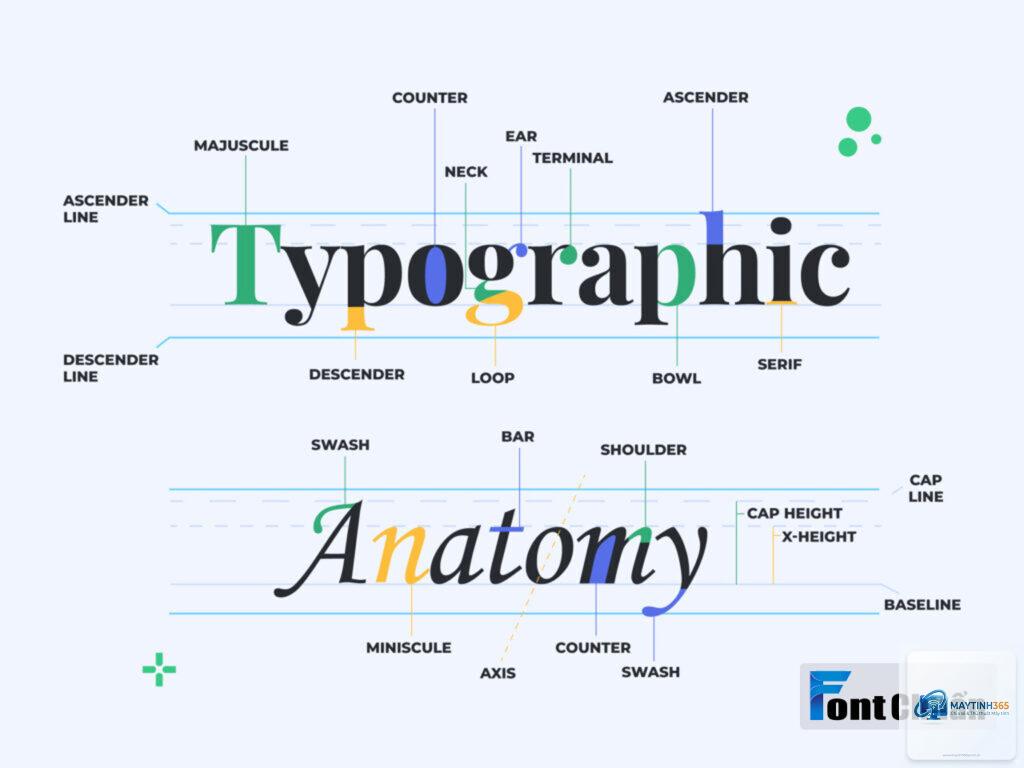
Cách cá nhân hóa font chữ để tạo dấu ấn riêng cho website và thương hiệu
Cá nhân hóa font chữ không chỉ đơn thuần là thay đổi kiểu chữ trên màn hình. Đây là một chiến lược thiết kế giúp thương hiệu truyền tải cá tính, tăng nhận diện và cải thiện trải nghiệm người dùng. Trong thời đại mà hàng triệu website cạnh tranh nhau từng giây, việc sở hữu một bộ font chữ độc đáo có thể là yếu tố quyết định giữ chân khách truy cập. Bài viết này sẽ hướng dẫn bạn cách cá nhân hóa font chữ từ cơ bản đến nâng cao, áp dụng cho website, ứng dụng và nội dung số.
Cá nhân hóa font chữ là gì và tại sao cần thực hiện
Cá nhân hóa font chữ là quá trình tùy chỉnh kiểu chữ, kích thước, màu sắc, khoảng cách và các thuộc tính khác để phù hợp với mục đích sử dụng cụ thể. Không giống như việc chọn một font chữ mặc định từ hệ thống, cá nhân hóa đòi hỏi sự can thiệp sâu hơn vào cấu trúc thiết kế.
Mỗi font chữ mang một tâm trạng riêng. Font serif cổ điển tạo cảm giác trang trọng, font sans-serif hiện đại thể hiện sự tối giản, font script bay bướm gợi sự sáng tạo. Khi bạn cá nhân hóa font chữ, bạn đang chọn đúng giọng điệu để giao tiếp với khán giả mục tiêu.
Lợi ích rõ ràng nhất là tăng tỷ lệ nhận diện thương hiệu. Một nghiên cứu từ Đại học Loyola cho thấy màu sắc và kiểu chữ nhất quán có thể tăng nhận diện thương hiệu lên đến 80%. Khi người dùng nhìn thấy font chữ quen thuộc, họ lập tức liên tưởng đến thương hiệu của bạn.
Các yếu tố cốt lõi trong cách cá nhân hóa font chữ
Lựa chọn kiểu chữ phù hợp với bản sắc thương hiệu
Bước đầu tiên trong cách cá nhân hóa font chữ là xác định tính cách thương hiệu. Một thương hiệu công nghệ sẽ phù hợp với font sans-serif như Roboto hay Inter. Trong khi đó, thương hiệu thời trang cao cấp có thể chọn font serif thanh lịch như Playfair Display.
Không nên sử dụng quá ba font chữ trên một trang web. Sự kết hợp lý tưởng thường là một font cho tiêu đề, một font cho nội dung chính và một font cho các yếu tố nhấn mạnh. Sự nhất quán này giúp người đọc không bị rối mắt và duy trì trải nghiệm mượt mà.
Tùy chỉnh kích thước và khoảng cách chữ
Kích thước font chữ ảnh hưởng trực tiếp đến khả năng đọc. Văn bản trên màn hình máy tính nên có kích thước tối thiểu 16px, trong khi trên thiết bị di động có thể cần lớn hơn. Khoảng cách dòng (line-height) lý tưởng là 1.5 đến 1.8 lần kích thước font để mắt có thể di chuyển dễ dàng.
Khoảng cách chữ (letter-spacing) cũng đóng vai trò quan trọng. Với font chữ in hoa, tăng nhẹ letter-spacing giúp chữ dễ đọc hơn. Với font chữ thường, giữ khoảng cách mặc định hoặc giảm nhẹ tạo cảm giác hiện đại.
Màu sắc và độ tương phản
Màu sắc font chữ cần đảm bảo độ tương phản đủ cao với nền. Tỷ lệ tương phản tối thiểu 4.5:1 cho văn bản thường và 3:1 cho văn bản lớn theo tiêu chuẩn WCAG. Màu đen trên nền trắng là an toàn nhất, nhưng family=Roboto:wght@400;700&display=swap” rel=”stylesheet”>
Tạo font chữ tùy chỉnh bằng công cụ thiết kế
Nếu muốn font chữ hoàn toàn độc nhất,
Làm thế nào để kiểm tra font chữ hiển thị tốt trên mọi trình duyệt?
Sử dụng công cụ BrowserStack hoặc LambdaTest để kiểm tra trên nhiều trình duyệt và hệ điều hành. Đảm bảo khai báo font fallback trong CSS để nếu font chính không tải được, trình duyệt sẽ dùng font dự phòng.
Cá nhân hóa font chữ có ảnh hưởng đến SEO không?
Font chữ không ảnh hưởng trực tiếp đến SEO nhưng gián tiếp qua trải nghiệm người dùng. Font chữ khó đọc làm tăng tỷ lệ thoát, giảm thời gian ở lại trang, từ đó ảnh hưởng tiêu cực đến thứ hạng. Ngược lại, font chữ dễ đọc và đẹp mắt giữ chân người dùng lâu hơn.
Có cần phải biết code để cá nhân hóa font chữ không?
Không nhất thiết. Các nền tảng như WordPress, Wix, Squarespace cung cấp giao diện trực quan. Tuy nhiên, để có kết quả tối ưu và linh hoạt, kiến thức cơ bản về HTML và CSS là lợi thế lớn.
Lưu ý quan trọng khi thực hiện cá nhân hóa font chữ
Luôn ưu tiên tốc độ tải trang. Font chữ tùy chỉnh có thể làm chậm website nếu không tối ưu. Sử dụng định dạng WOFF2, nén font, và chỉ tải các trọng lượng cần thiết. Công cụ Google PageSpeed Insights giúp đánh giá tác động của font lên hiệu suất.
Bắt đầu bằng cách xác định tính cách thương hiệu, sau đó chọn font chữ phản ánh đúng giá trị đó. Sử dụng các công cụ có sẵn như Google Fonts cho người mới bắt đầu, và tiến dần đến thiết kế font riêng khi đã có kinh nghiệm. Luôn kiểm tra khả năng đọc, tốc độ tải và tính nhất quán trên mọi nền tảng.
Với cách cá nhân hóa font chữ đúng đắn, bạn không chỉ tạo ra một website đẹp mắt mà còn xây dựng một thương hiệu mạnh mẽ, dễ nhận diện và đáng tin cậy trong mắt khách hàng.